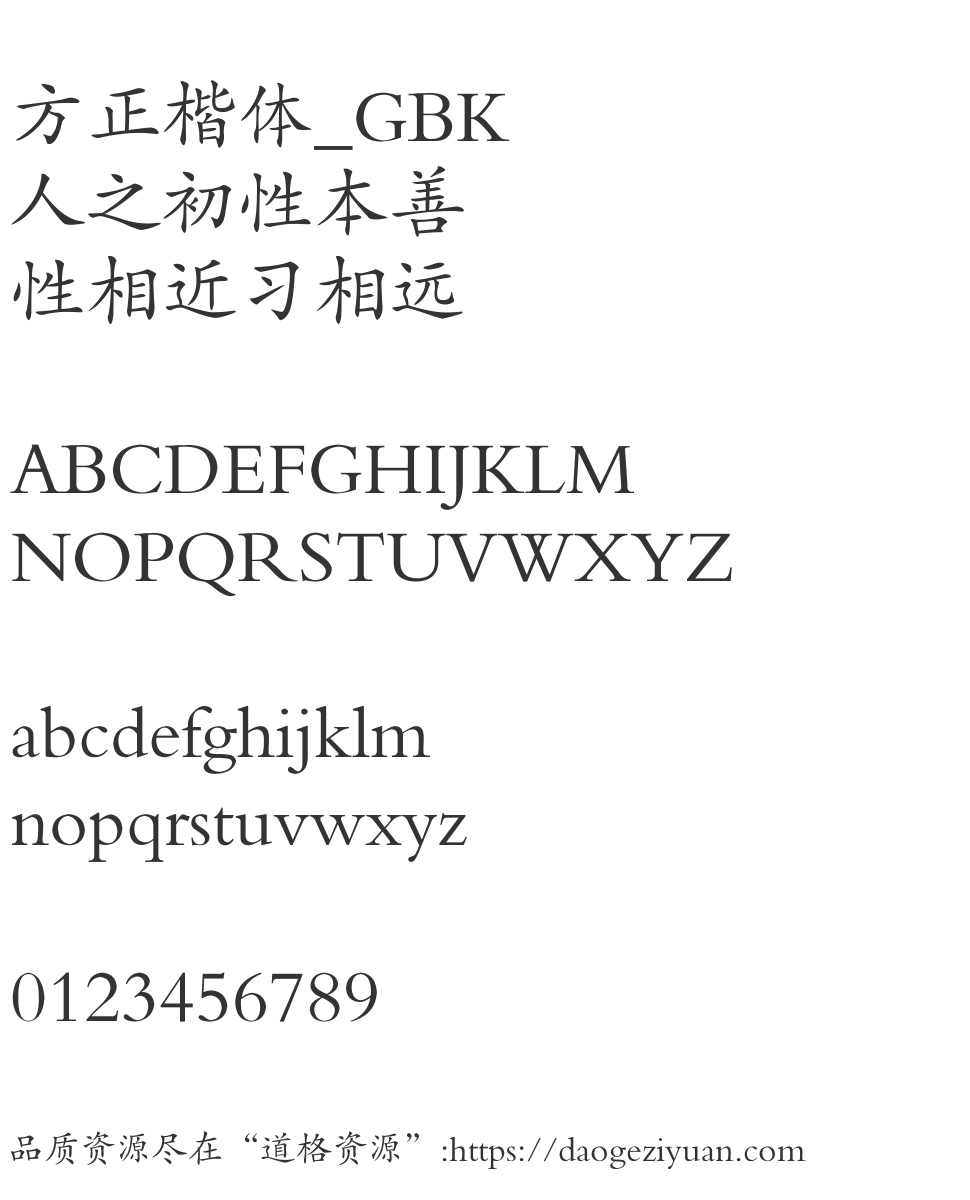
方正楷体_GBK字体是一种优秀的楷书字体,由方正字库设计制作。该字体采用了传统楷书的写法,造型端庄、清秀,书法笔画流畅自然,具有浓郁的中国传统文化气息。方正楷体_GBK字体广泛应用于书法、印刷、广告设计、品牌标志等领域,适用于各种中文排版需求。该字体还支持GBK编码,可以完美显示中文文字内容,是一款非常实用的字体工具。文件名:方正楷体_GBK
方正楷体_GBK是一款非常不错的手写艺术字体,具有很好的视觉感,适合于文化类的宣传设计、商业类品牌的广告和产品包装设计以及个性化文字排版等较多场景。